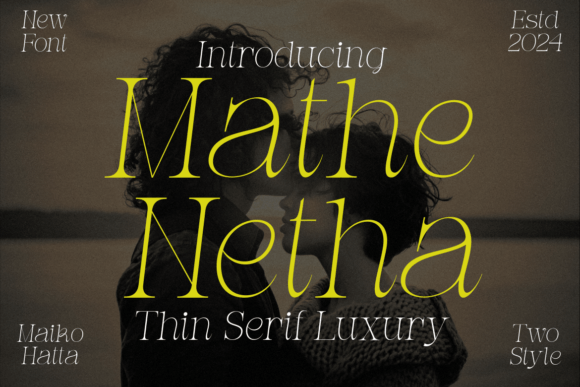
Mathe Netha
หากคุณกำลังมองหาเนื้อหาคุณภาพสูงเช่น Mathe Netha แพ็คเกจพรีเมียมนี้เป็นตัวเลือกที่ยอดเยี่ยมสำหรับโปรเจ็กต์สร้างสรรค์ของคุณ
ไม่ว่าคุณจะสร้างผลิตภัณฑ์ POD (Print on Demand) คำเชิญงานแต่งงาน หรือกราฟิกโซเชียลมีเดีย Mathe Netha ก็เหมาะสมอย่างยิ่ง